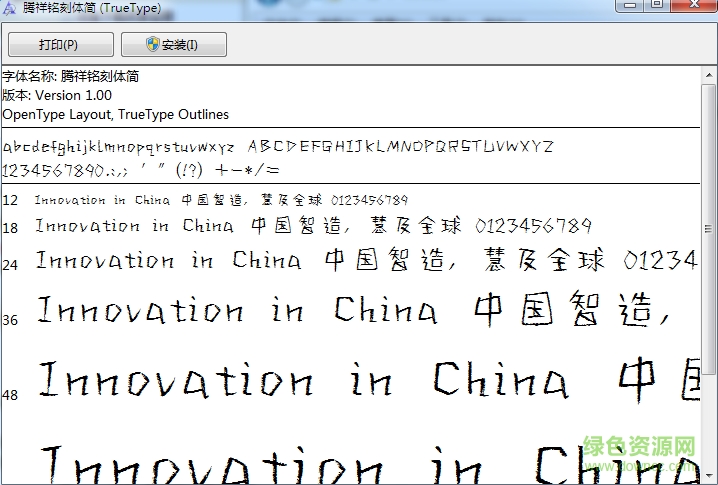
騰祥銘刻體簡(jiǎn)是一款非常有特色的電腦字體,字形大小有別;筆畫粗細(xì)有致,看似不經(jīng)意卻實(shí)則有意而為之,在經(jīng)意與不經(jīng)意間尋求平衡,浸透設(shè)計(jì)師書寫功力。本作品可適用于包裝設(shè)計(jì)、廣告設(shè)計(jì)、網(wǎng)頁(yè)設(shè)計(jì)等。有需要就來綠色資源網(wǎng)下載!
騰祥銘刻體簡(jiǎn)由設(shè)計(jì)師孔淼先生書寫設(shè)計(jì),風(fēng)格鮮明、特點(diǎn)突出。筆畫古樸雅拙、精雕細(xì)刻。筆畫猶如用刀在石壁上一筆筆刻畫出的圖案。筆筆勁力、力透紙背、飛白顯露,彰顯刀刻之功。